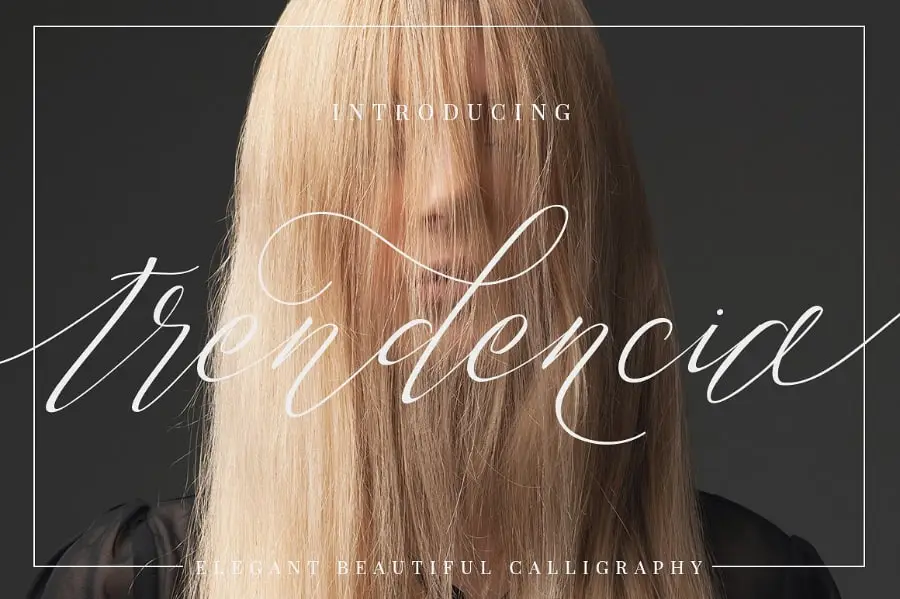
Trendencia Script Font
Introduzimos a nova fonte em script, Trendencia Script Font, criada e compartilhada pela Dirtyline Studio. Este estilo elegante de chisel é uma fonte de calligrafia que destaca-se com seu deslizamento linha após linha suave, traços clássicos e toques elegantes. É perfeitamente adequado para várias aplicações, incluindo assinaturas, logotipos, cartas de boletim, convites de casamento, adesivos, placas de sinalização, materiais de embalagem, noticiários, posters e outros materiais. O Trendencia Script Font oferece um toque sofisticado que se encaixa perfeitamente em qualquer projeto de design gráfico em busca de uma combinação suave entre elegância e modernidade.